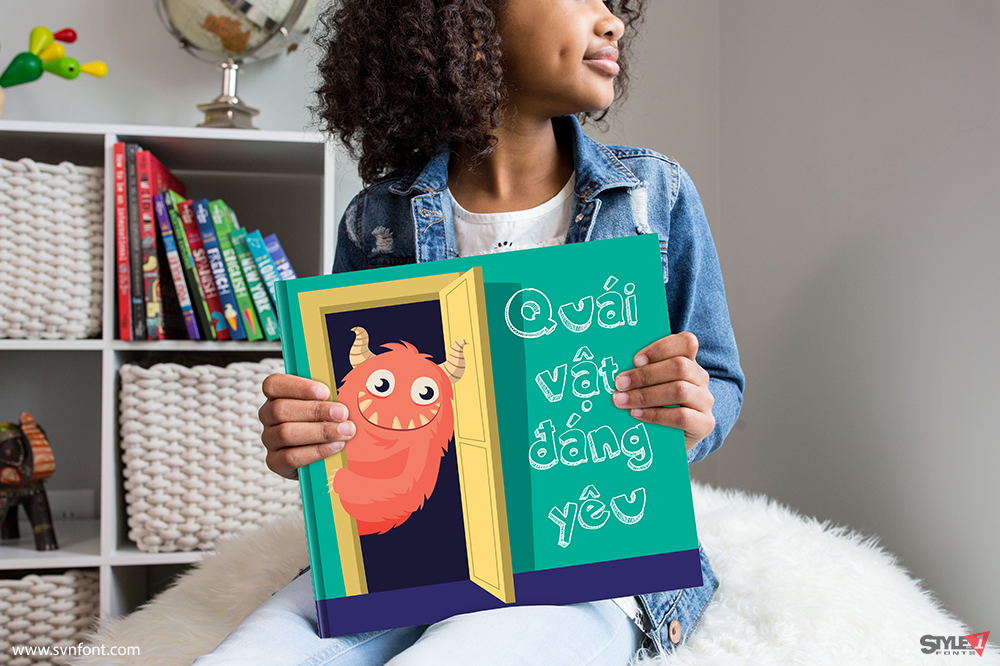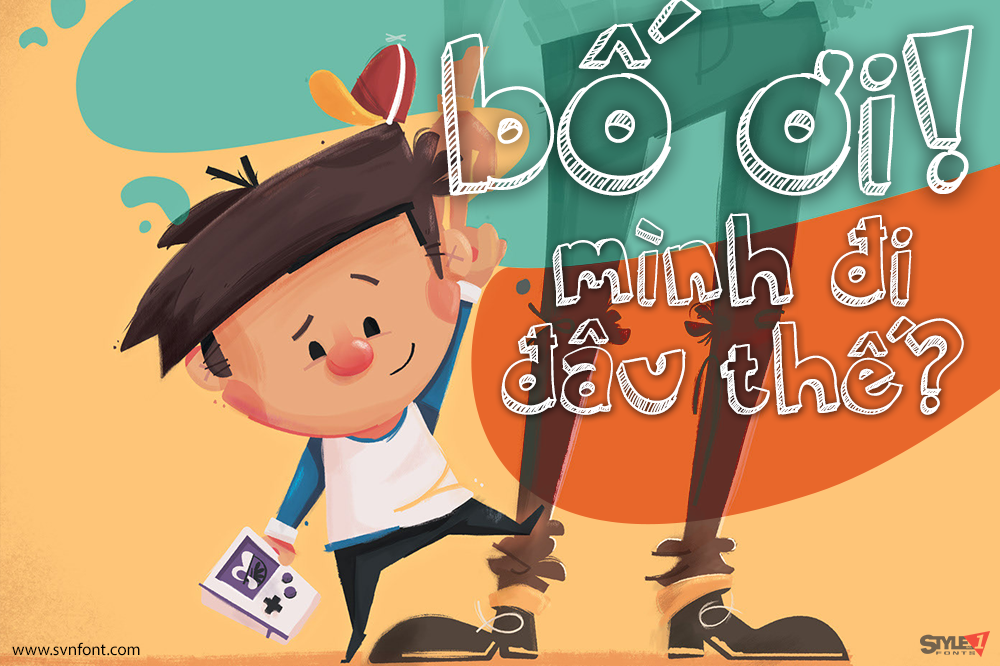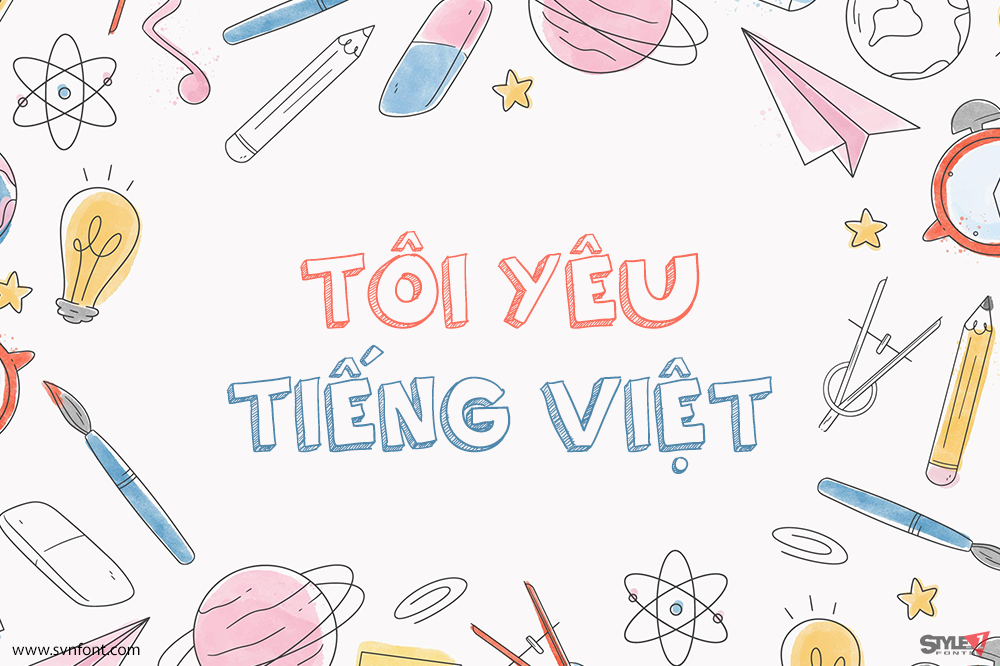
Doodly là một font viết tay hiệu ứng phấn viết trên bảng. Mỗi ký tự được thiết kế tỉ mỉ, giữ nguyên đặc điểm nghệch ngoạc của phấn vẽ, vừa đẹp mắt, vừa tinh nghịch. Font thích hợp cho thiết kế về học đường, bảng hiệu, trang trí, trẻ em… Hãy thoải mái vui chơi với font này và dùng nó theo bất kỳ cách nào bạn thích!
Nhà thiết kế: RZDESIGN
Nhà phát hành: RZDESIGN